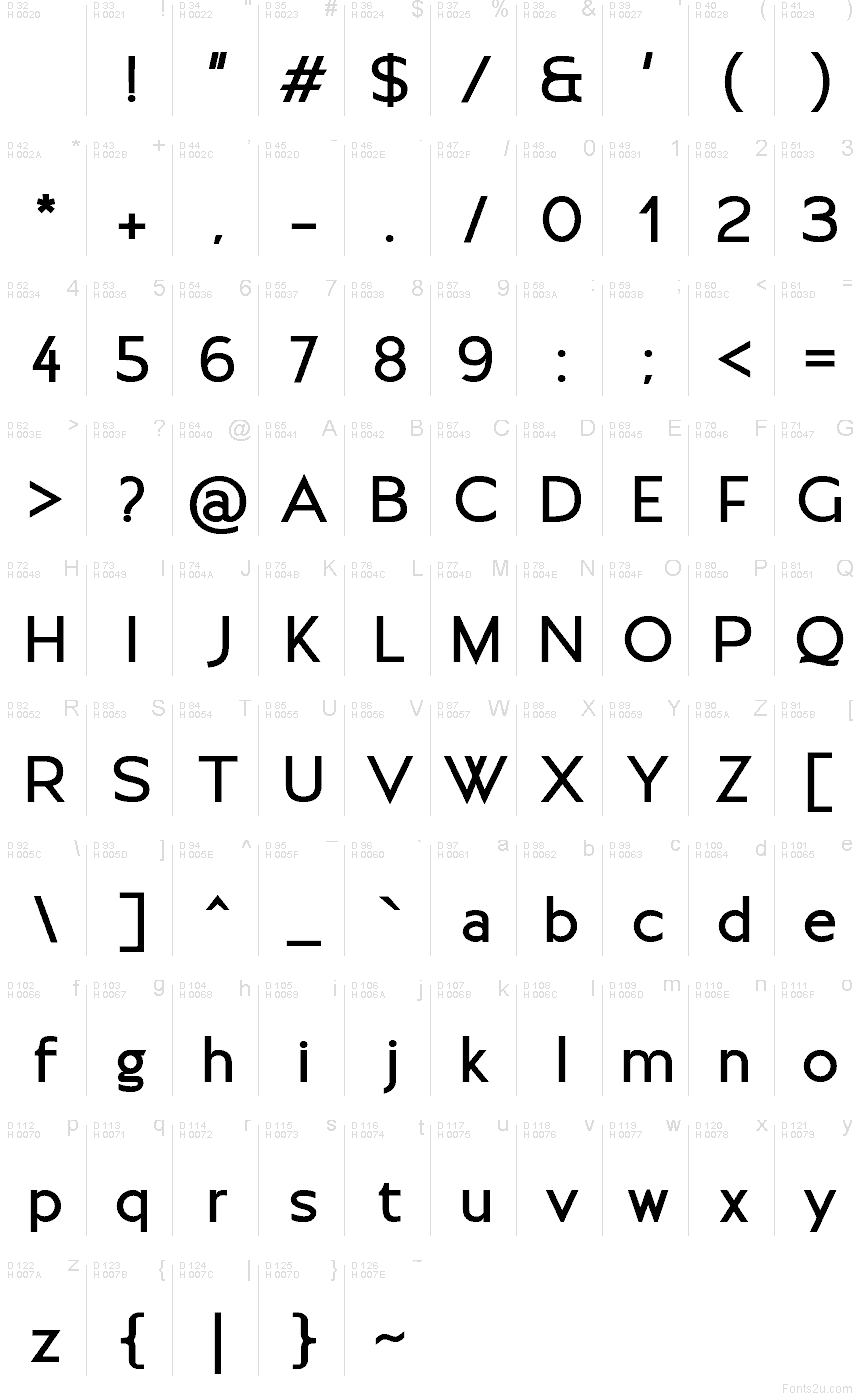
Písmo Moirest Bold od Muhamada Fikry Nuralifa z Fikryal Studio je bezplatný bezpatkový font, který působí moderně a sebevědomě, aniž by byl chladný. Tvary jsou čisté a široké s vyrovnaným rytmem, což dodává slovům plynulou váhu vhodnou pro loga, která zůstává čitelná i při zvětšení. Má ostrý, dotažený vzhled, který se nachází někde mezi technickým stylem a přátelskostí.
S Moirest Bold dosáhnete výrazných výsledků u značek, záhlaví aplikací, hlavních titulků na webových stránkách, obalů, příspěvků na sociálních sítích, redakčních citátů a plakátů. Tento bezplatný font také dobře funguje v orientačních systémech, kde záleží na jasnosti. Kombinujte jej s klidným humanistickým sans-serifem nebo neutrálním patkovým písmem v hlavním textu a nechte Moirest Bold vyniknout v nadpisech.